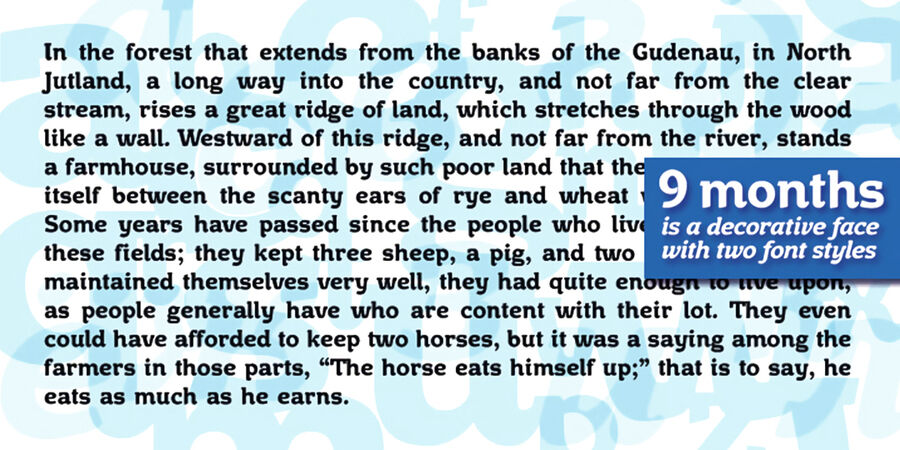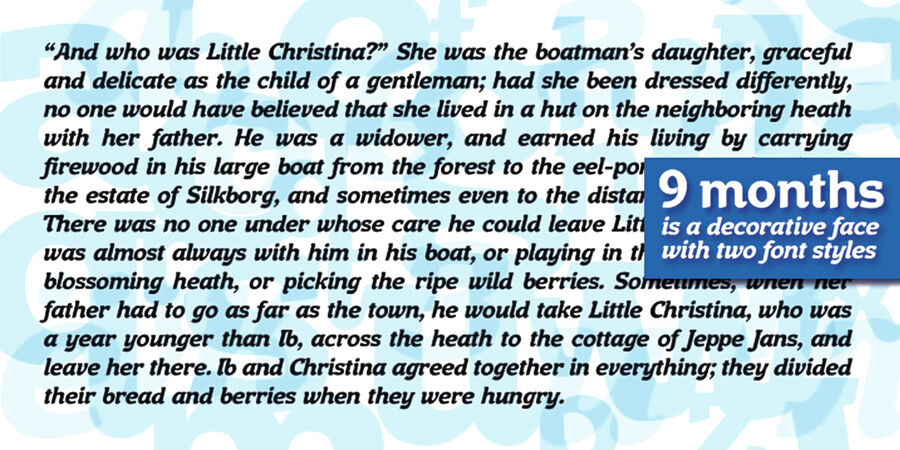
9 months — декоративний шрифт із двома накресленнями. Він гарно виглядатиме на упаковках для їжі, особливо, солодощів, у дитячих книжках і журналах.
Ця робота присвячена періоду в житті моєї дружини, коли вона протягом 9 місяців виношувала нашу доньку.
Шрифт розробив Кирило Ткачов у 2009–2010 роках.
2 накреслення
Асоціації з сімейством шрифтів 9 MonthsОсобистість і характер гарнітури:
М'який, затишний, помірний, спокійний, стабільний, стійкий, універсальний, ввічливий, інтелігентний, комфортний, гладенький, мирний, доброзичливий, ясний, статичний, стриманий, сучасний, екологічний, зелений, гармонійний, органічний, красивий, пластичний, гнучкий, приємний, добрий, культурний, акуратний, оптимістичний, неквапливий, соковитий, милий, весняний, сімейний, святковий, домашній, смачний, свіжий, довірчий, літній, теплий, якісний, гарненький, симпатичний, природний, натуральний, дівчачий
— Гарнітура асоціюється з віком: